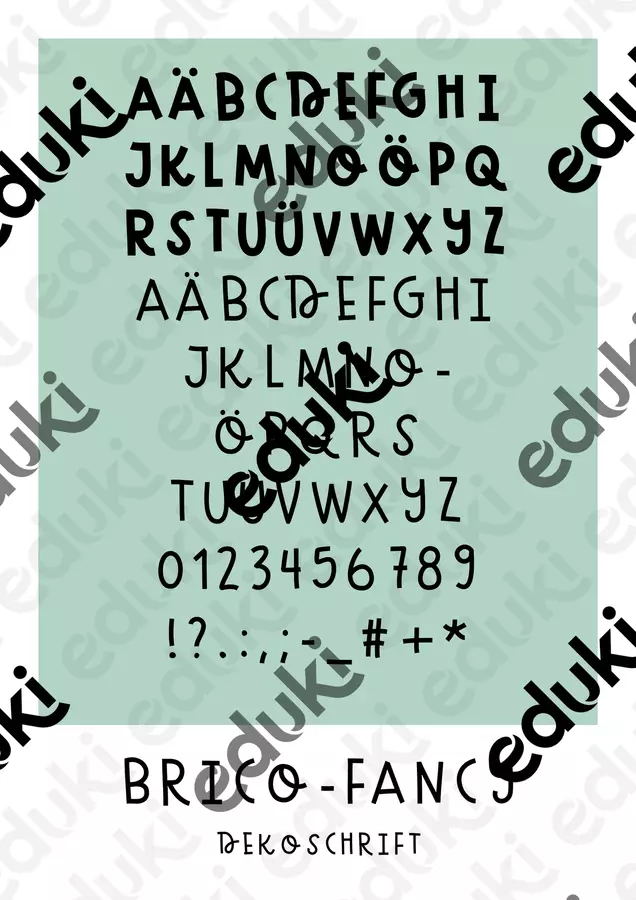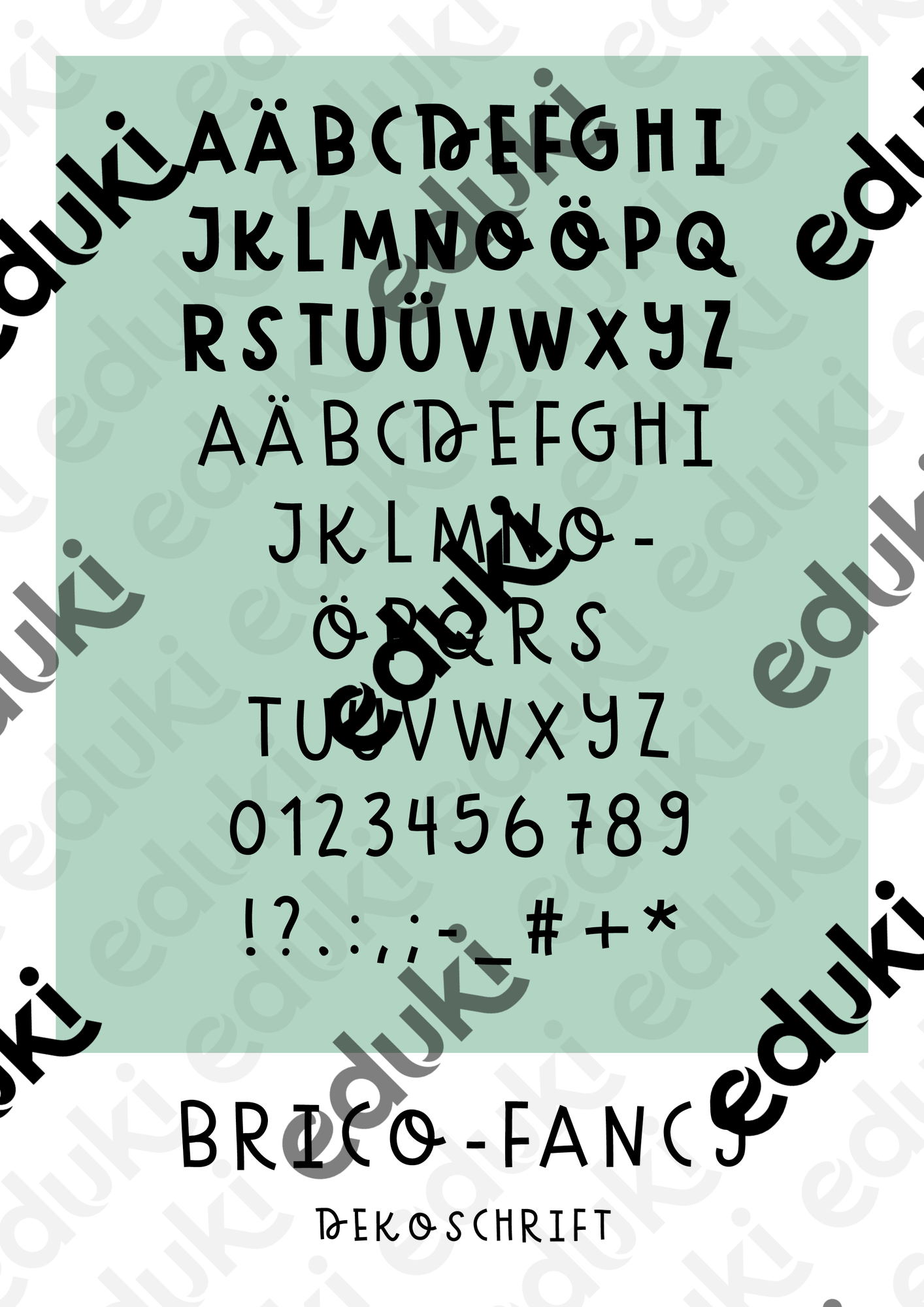
Selbsterstellte Dekoschrift die sich wunderbar zur Erstellung von Arbeitsblättern oder anderem Unterrichtsmaterial eignet.
Schriftart für dein Arbeitsmaterial - BricoFancy